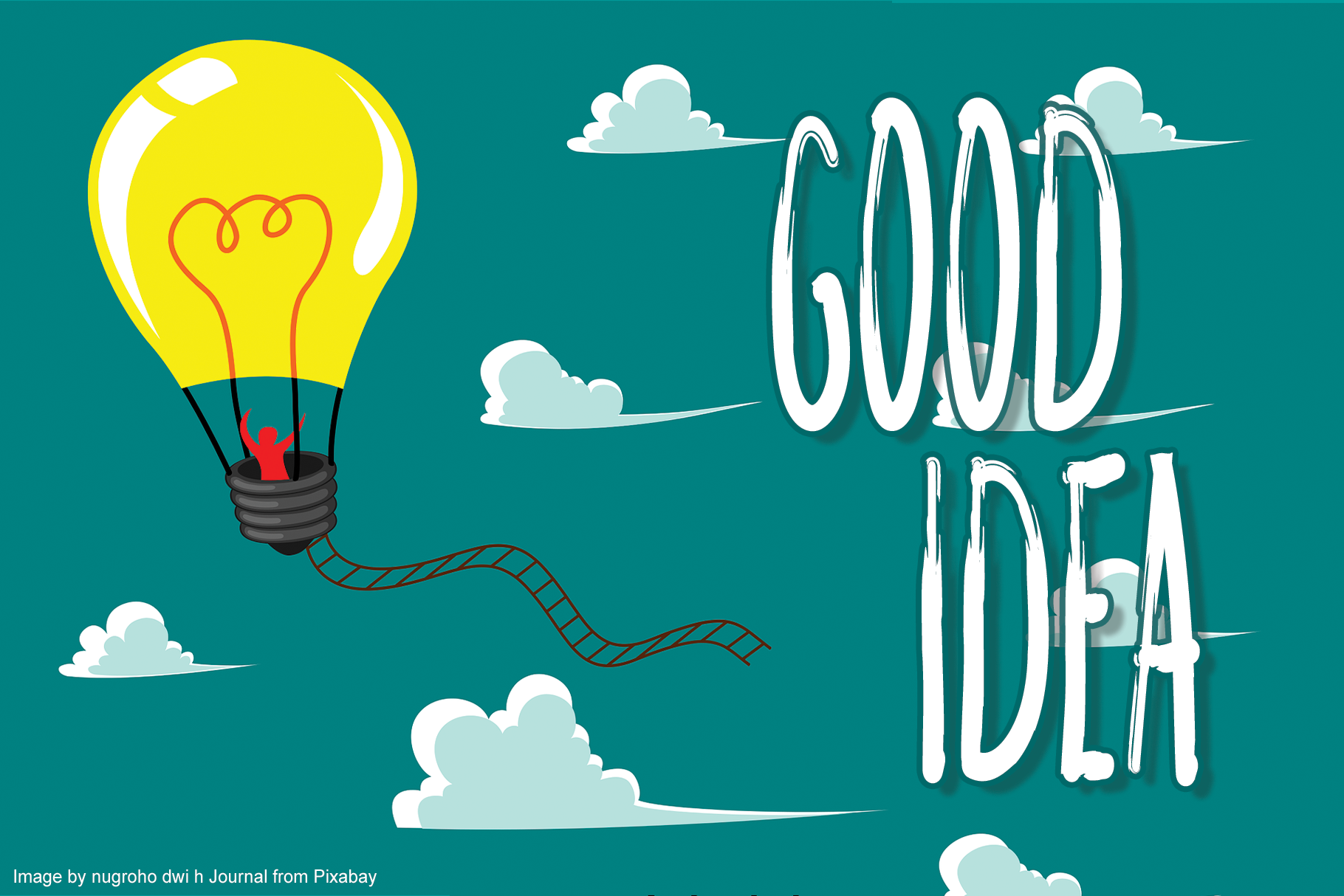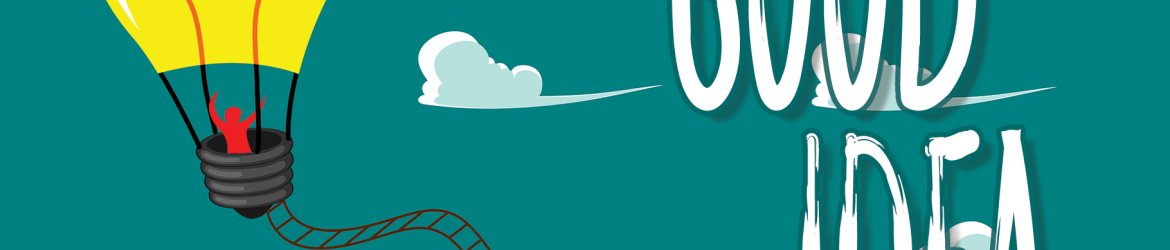
A ‘Good Idea Font’ é uma elegante seleção para os projetistas que buscam dar vida a designs criativos e modernos. Essa tipografia Display oferece uma mistura única de frescor e elegância, ideal para qualquer aplicação que exija um toque sofisticado. Seja para texturas animadas em histórias infantis, criações para os amantes da cultura pop ou slogans memoráveis no design editorial, a ‘Good Idea Font’ é perfeita. Ela também é uma escolha ideal para títulos de produtos e marcas, capas de livros, outdoors e até mesmo as mais variadas obras de arte digitais. Em sua forma atualizada pelo designer el hotcig, essa fonte oferece uma personalidade própria que enriquece qualquer projeto visual.